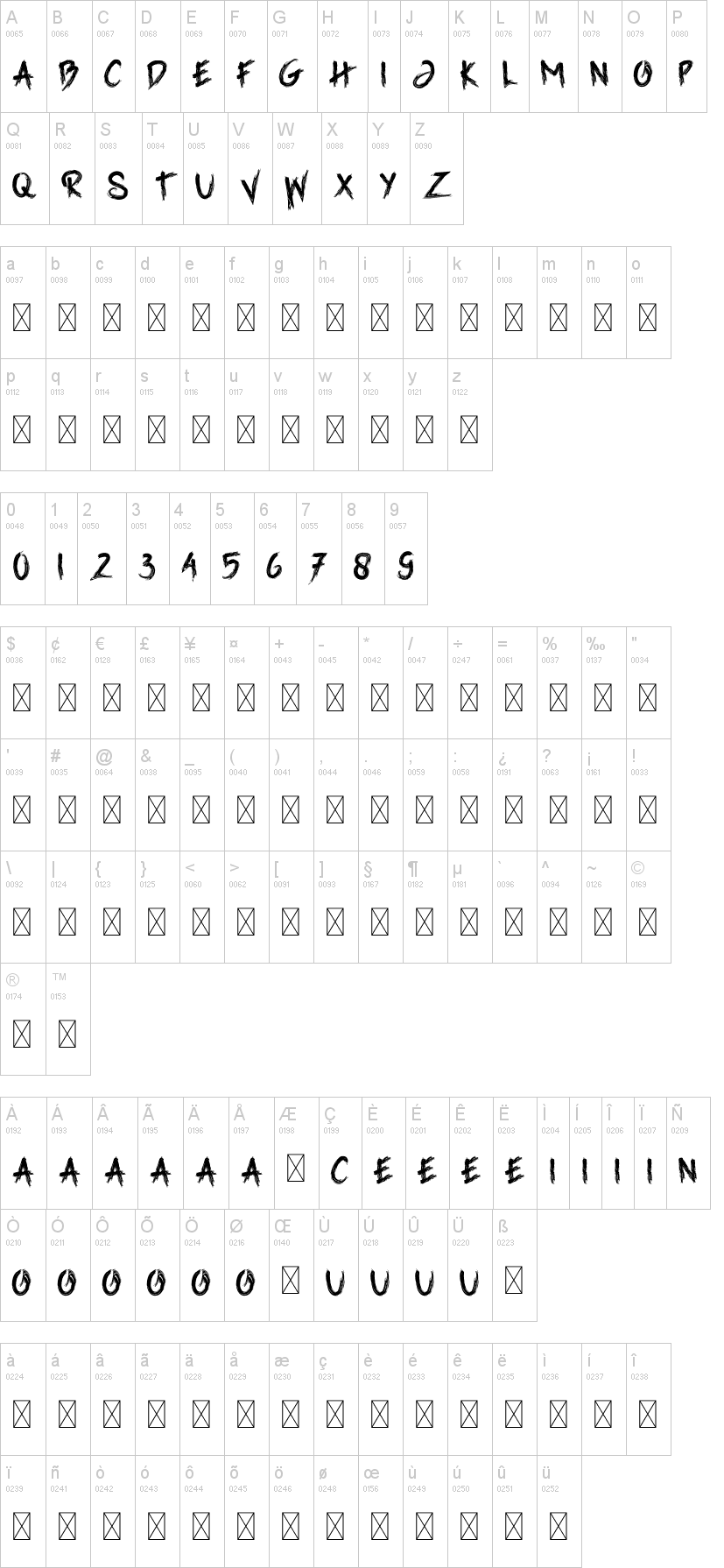
Grim Reaper 字体是一种创意艺术字体,以“死神”为主题设计而成。它的形状独特、充满神秘感,字母的笔画和线条都仿佛是由一把锋利的镰刀所刻画而成。 这种字体通常用于设计书籍封面、海报、插画、音乐封面、Halloween 主题设计等场合,以营造一种神秘、恐怖、诡异的氛围效果。 Grim Reaper 字体有多种变体,包括不同大小写字母、数字和标点符号,可以根据设计师的需要自由组合和调整。尽管这种字体并不适合所有场合,但在适当的设计中,它可以呈现出一种独特的视觉效果。内容介绍
Grim Reaper是一款非常不错的手写艺术字体,具有很好的视觉感,适合于文化类的宣传设计、商业类品牌的广告和产品包装设计以及个性化文字排版等较多场景。